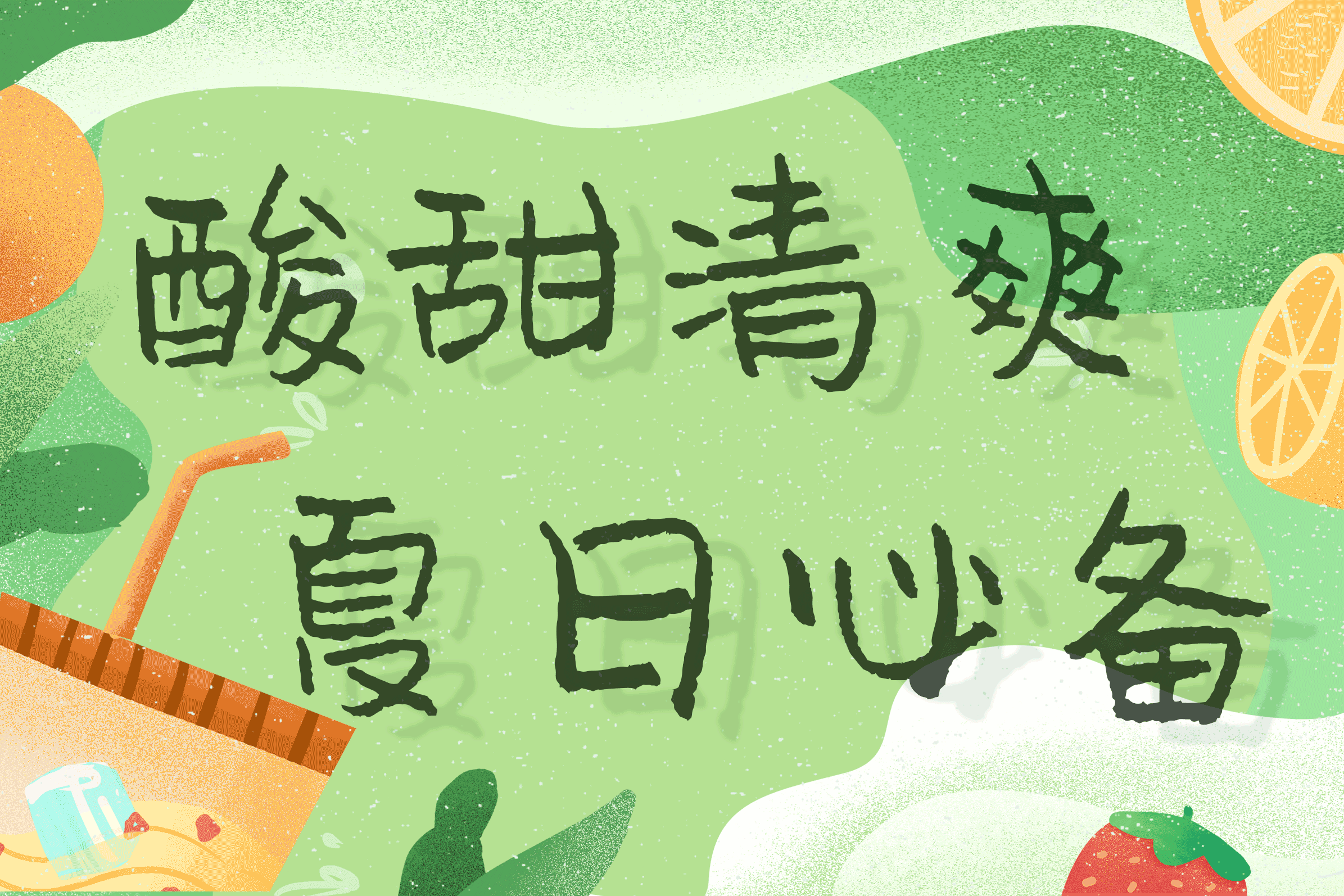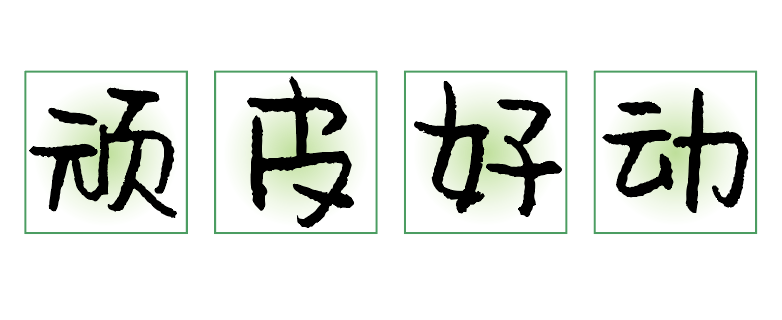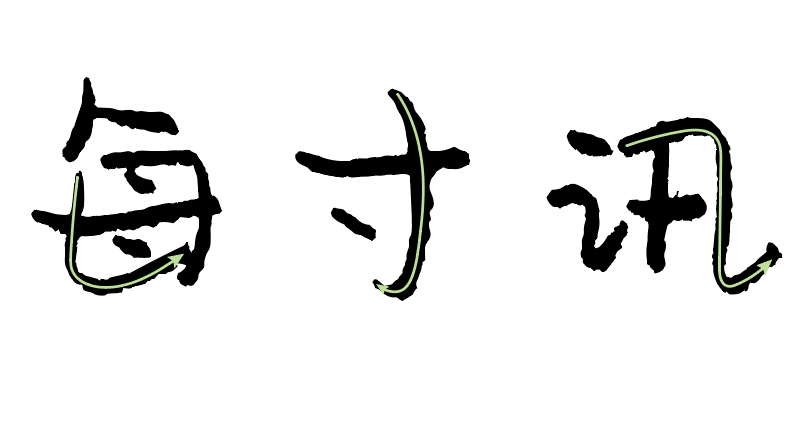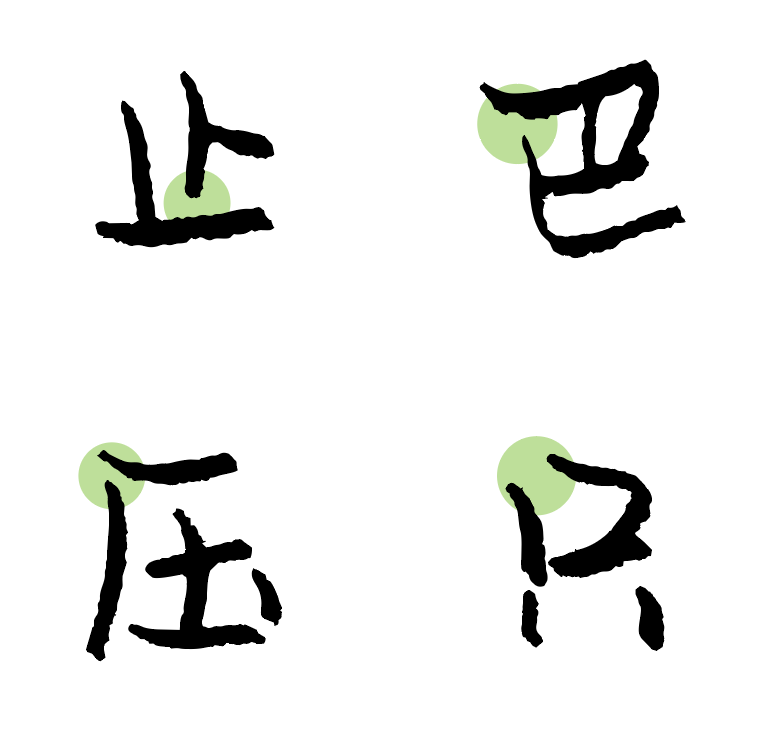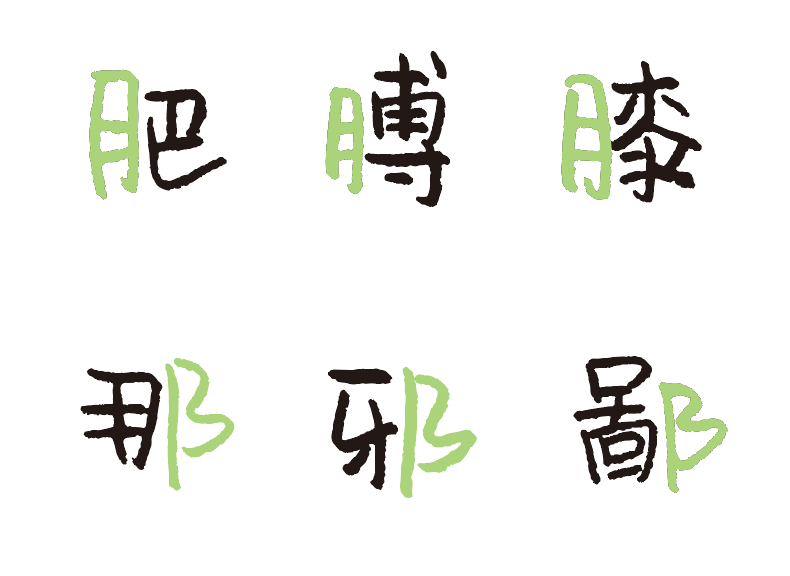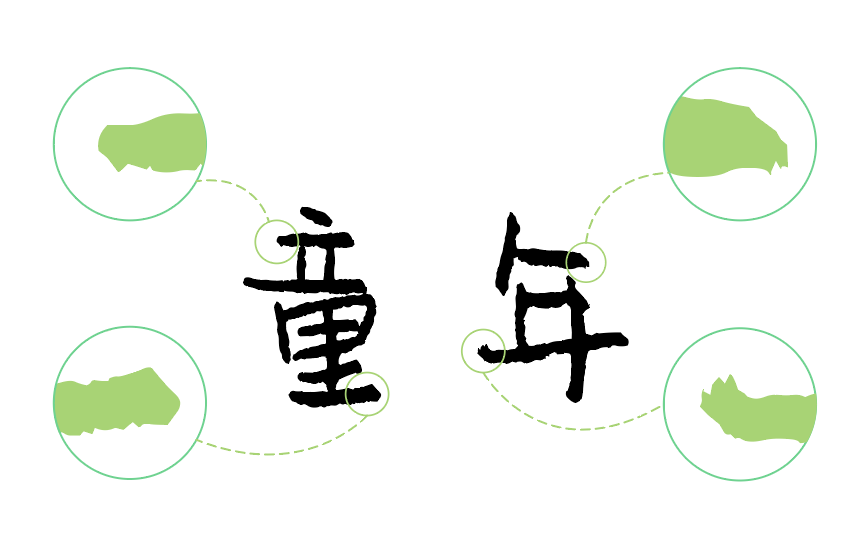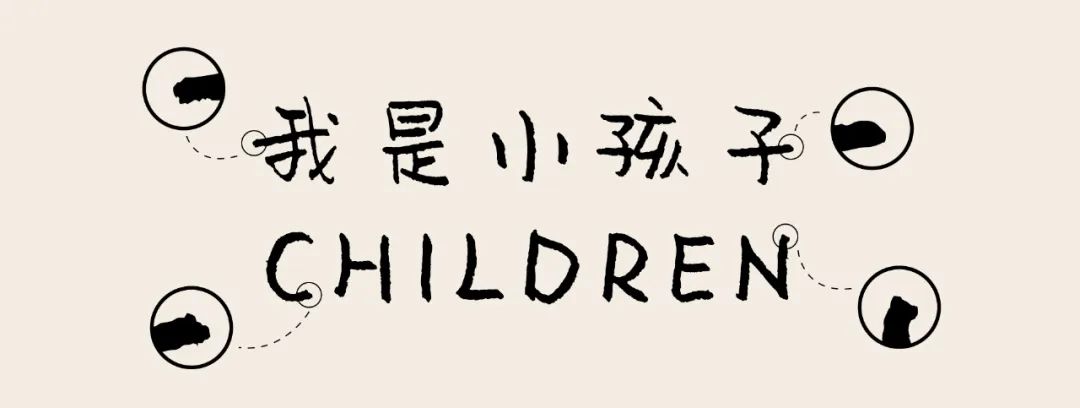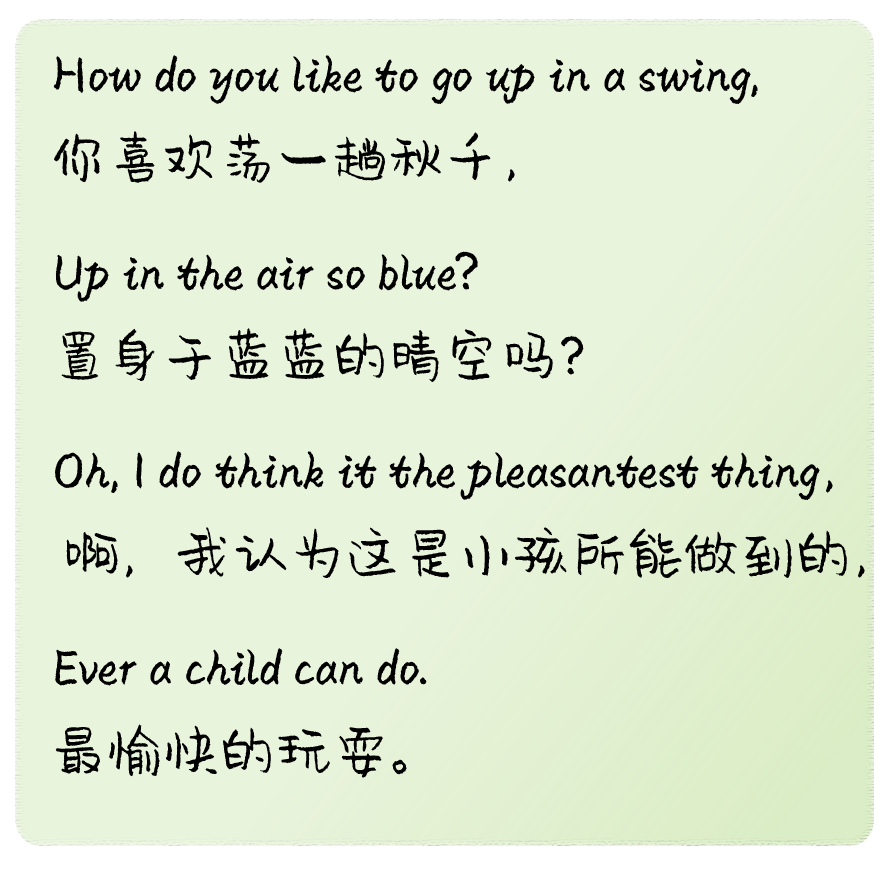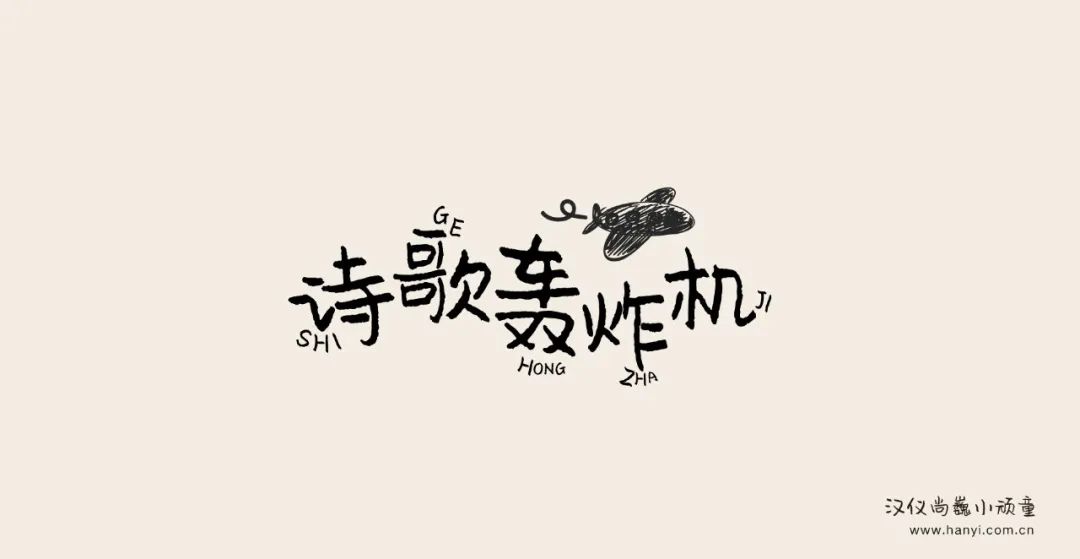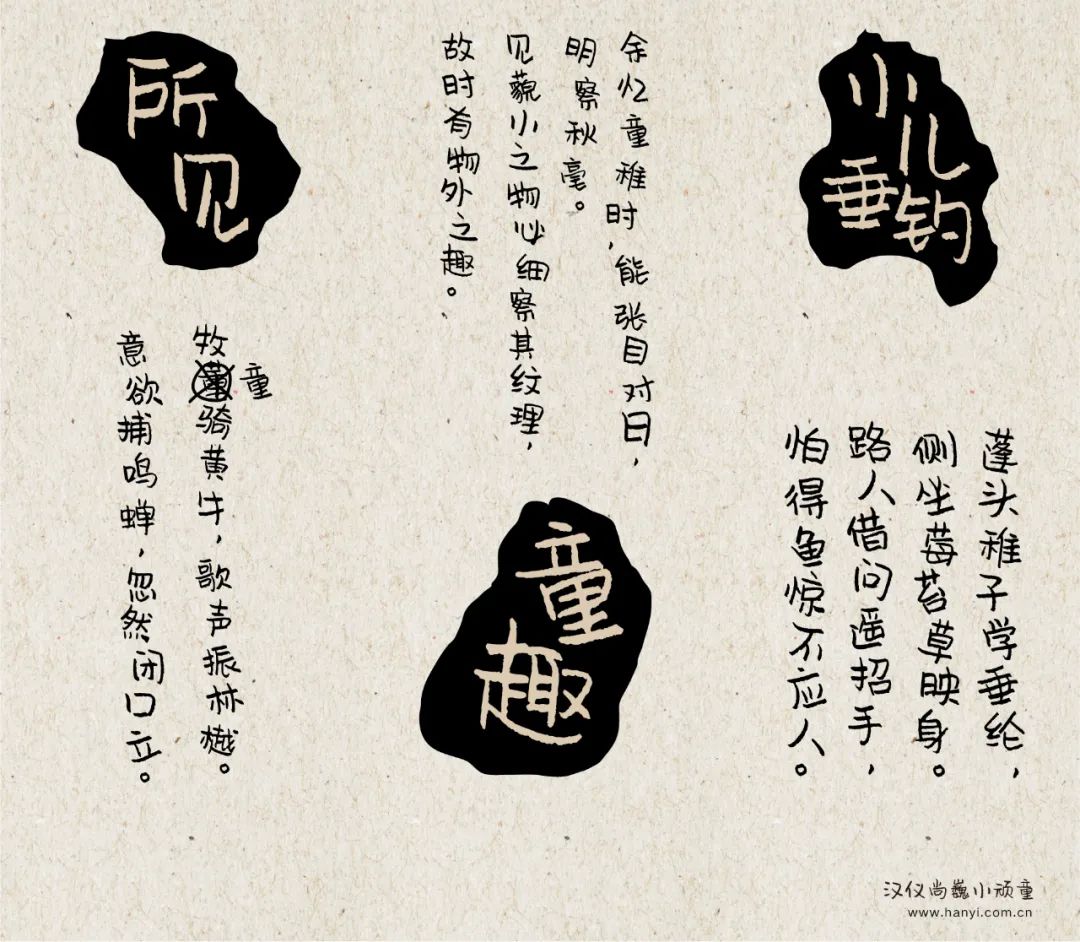
汉仪尚巍小顽童字体介绍,一款可爱风格的硬笔字体
整体特点
“汉仪尚巍小顽童”是由90后新锐字体设计师尚巍倾力打造的一款可爱风格的硬笔字体。这款字体字形可爱,笔画童稚,结构圆润放松,透着年幼的单纯稚气,给人温暖又开心的视觉感受,非常具有亲和力。
字形特点
“汉仪尚巍小顽童”字形偏方,中宫较大,笔画简洁而不呆板,使字体呈现出呆萌可爱,调皮好动的样子。
笔画特征
“汉仪尚巍小顽童”的转折圆润,笔画有着细腻的弧线曲度,使充满童趣的手写体更加精致。
“汉仪尚巍小顽童”在笔画衔接处的留白让人联想到儿童在写字时的笨拙可爱,给予了字体与众不同的透气感和呼吸感,生命力表现十足。
“汉仪尚巍小顽童”保留了手写的独创性,减少机械复制,笔画活泼生动,使相同的偏旁出现不同的手写效果。
“汉仪尚巍小顽童”还保留了笔墨与纸张接触后富有变化的纹理,多了一份天真质朴。
中西文匹配
“汉仪尚巍小顽童”的西文融入了中文书法的手写方式,笔触丰富,运笔流畅,手写感强,弹性十足。中、西文搭配使用时呈现出更佳的视觉效果。
字体应用